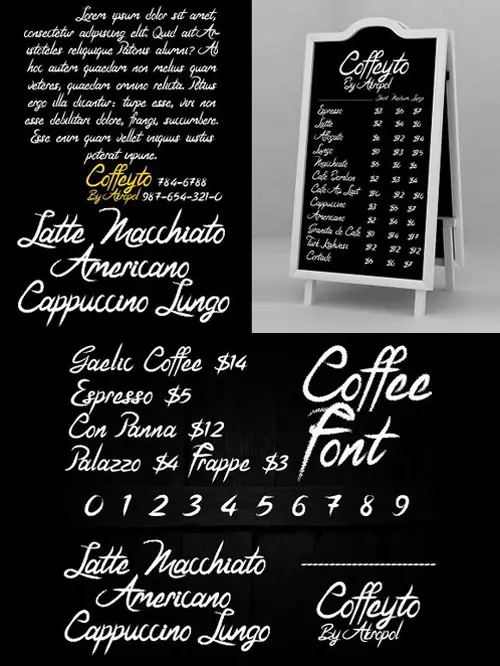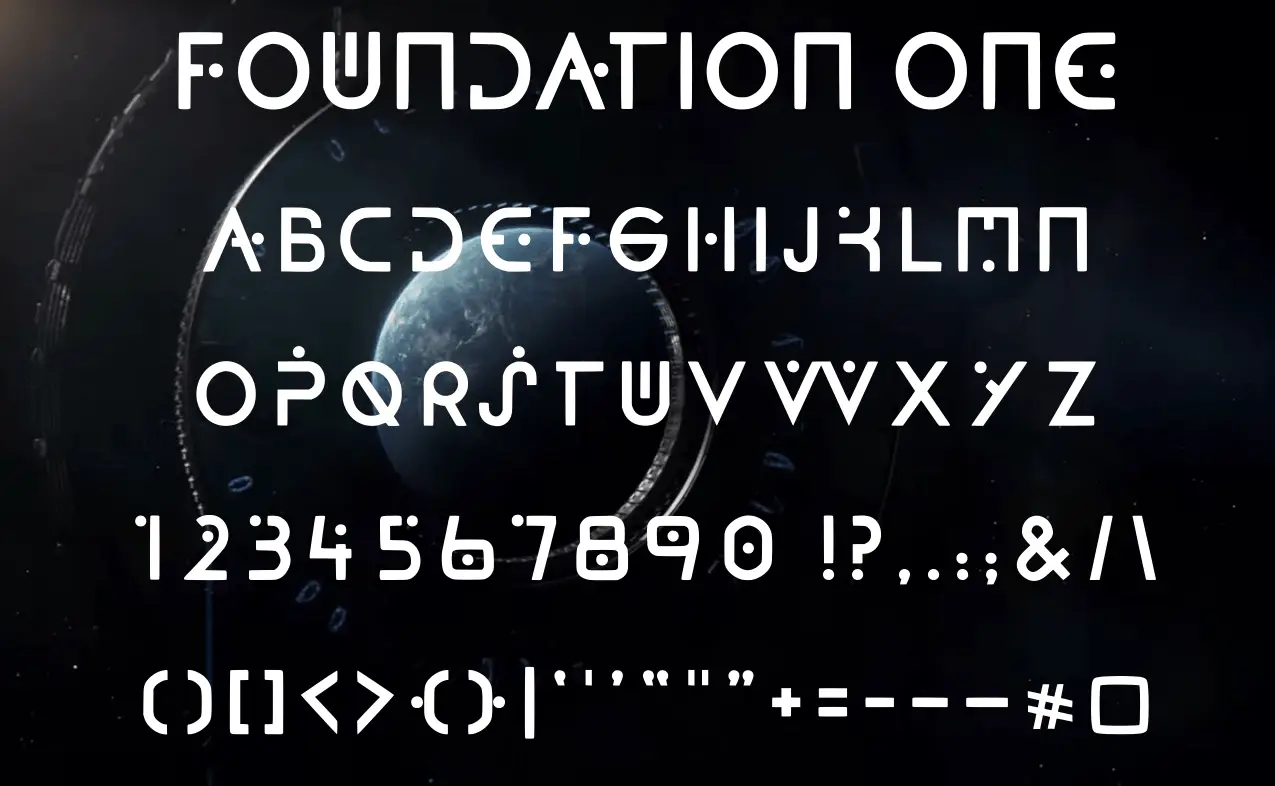
嘿,创意灵魂,你好呀!👋 准备好一头扎进字体与设计素材的宝库了吗?我们无比激动地向你揭晓 BrushesPack 系列第105弹——这是一套精心挑选的20款惊艳字体与设计元素,绝对能让你的下一个项目火力全开。🚀 无论你是在设计婚礼请柬、打造大胆的品牌形象,还是只是想用俏皮字体玩玩,这个系列都能满足你的需求。
从优雅的书法字体(低语着精致)到大胆的展示字体(高喊着引人注目),这一系列充满了个性。所以,拿起你最喜欢的饮料 ☕,舒服地坐下,让我们一起探索这些宝藏吧! ✨
为什么要使用这些字体与设计素材? 🎯
在设计的世界里,字体是你视觉故事的声音。合适的字体能将平淡的布局转变为杰作,唤起恰到好处的情感,并让你的品牌令人难忘。这个系列提供了极大的多样性——从通用的矢量图形和模板,到惊艳的衬线字体和手写字体——确保你为每次场合都拥有完美的工具。告别设计瓶颈,迎接无尽的灵感吧! 🌟
BrushesPack 系列第 105 期精选前 20 名
Garlicha 书法字体
用 Garlicha 为你的设计增添一份纯粹的优雅!这款流畅的手写字体非常适合邀请函、标志以及任何需要个人艺术气息的场合。✨ 它支持多种字重和多语言,用途广泛,堪称全能选手。
Coolline
想要一款超级百搭的设计工具?Coolline 就是你的新宠!🎨 这套高质量设计素材集非常适合品牌设计、营销物料和数字内容,堪称你创意工具箱中的瑞士军刀!
Enchanting Script Font
名副其实,这款字体极具魔力!🪄 其流畅的曲线与现代感的结合,非常适合令人惊艳的品牌设计、吸睛的标志以及优雅的邀请函。它包含所有所需字符,助您俘获观众的心。
Cinemathic Visualation 手写字体
为你的项目注入电影感!🎬 这款精美的手写字体,融合优雅曲线与现代格调,非常适合品牌设计、标识及印刷物料,让你的文字成为视觉焦点。
First Line 手写字体
用这款独特的手写字体为你的作品注入亲切、温暖的氛围!✍️ 它模仿了自然手写的流畅感,非常适合温馨的品牌设计、贺卡或任何需要人情味的项目。就像是你写给观众的一封私人信件。
Font Coffeyto
融合优雅与现代魅力,非Coffeyto莫属!☕ 作为正文字体清晰易读,用作标题又足够时尚。这款字体适合品牌设计、网页设计和印刷品,流畅得就像清晨的咖啡。
Geolog Display 字体
用 Geolog 彰显大胆态度!🪨 其独特而干净的字形设计专为吸引目光而生。这款展示字体是品牌标识、标志和标题的强大工具,让它们脱颖而出。
Fierry 展示字体
用 Fierry 点燃你的设计!🔥 这款引人注目的展示字体具有醒目的外观,非常适合大胆的品牌设计和吸睛的标题。提供常规和粗体两种字重,格式包括 OTF、TTF 和 WOFF,适用于任何项目。
Gilbert Qualifi 衬线字体
优雅与可读性兼备!👔 Gilbert Qualifi 是一款精心设计的衬线字体,为任何项目增添一抹格调。无论是品牌设计、标志制作,还是网页与印刷设计,它都是理想之选。
Foundation One Display 字体
在坚实的基础上打造您的品牌!🏛️ 这款粗体、现代的展示字体专为 impactful 视觉传达而设计。它是创建引人注目的标题和标志的绝佳利器。
Fugres 字体
Fugres 的拿手好戏就是多才多艺!🎭 这款字体将优雅与现代设计融为一体,适用于品牌标识、网页设计、印刷品,甚至用户界面。它无论大小都清晰易读,并提供多种字重。
暗红宝石黑体字
用 Dark Ruby 感受哥特风格!🧛♂️ 这款惊艳的黑色字母字体捕捉了传统历史韵味,细节精致。非常适合为海报、标志和品牌设计增添大胆经典的格调。
Cillian
干净、现代,且时尚感十足!🖤 Cillian 以其流畅的线条和优雅的曲线带来现代气息。对于需要精致外观的品牌设计、网页设计和印刷品而言,这是一个绝佳选择。
Bubble Peanut 字体
是时候来点真正的乐趣了!🥜 Bubble Peanut 是一款俏皮、充满奇思妙想的字体,圆润的边角非常适合儿童读物、贺卡和欢乐的品牌设计。它保证能让您会心一笑!
Etnyca Display 字体
用 Etnyca 为您的作品增添一抹个性!🎭 这款醒目的显示字体非常适合品牌设计、标识和用户界面。其独特风格确保您的项目在众多作品中脱颖而出。
Fantac 显示字体
用 Fantac 大胆、时尚地表达你的态度!🦄 其独特的字形和优雅的曲线使其成为标题和品牌素材的绝佳选择。
Conter 显示字体
干净、现代,而且完全大胆!🥇 Conter 的时尚曲线和独特造型非常适合需要现代感的标题和宣传材料。
Demon 展示字体
用Demon释放一丝锋芒!😈 这款醒目、粗犷的字体专为吸引并掌控注意力而设计。非常适合需要暗黑、强大气场的品牌、海报和创意项目。
Effort Calligraphy Font(轻松手写字体)
让优雅变得毫不费力!🌸 这款精美的手写字体拥有流畅的笔画和精致的细节,同时依然清晰易读。非常适合为任何项目增添精致格调。
Castlena 字体
用 Castlena 的优雅为您的项目画上句号!👑 这款时尚衬线字体散发着精致感,非常适合品牌设计、标志和网页设计。它还支持多语言字符,使其成为一款全球性的设计资产。
结语 💎
这就是您本季终极创意伴侣的全部内容!从 Bubble Peanut 的俏皮曲线到 Castlena 的皇家精致,BrushesPack 系列第 105 部分 是一座字体宝藏的金矿。🪙 每件作品都旨在激发您的想象力、简化您的工作流程,并让您的作品真正令人难忘。